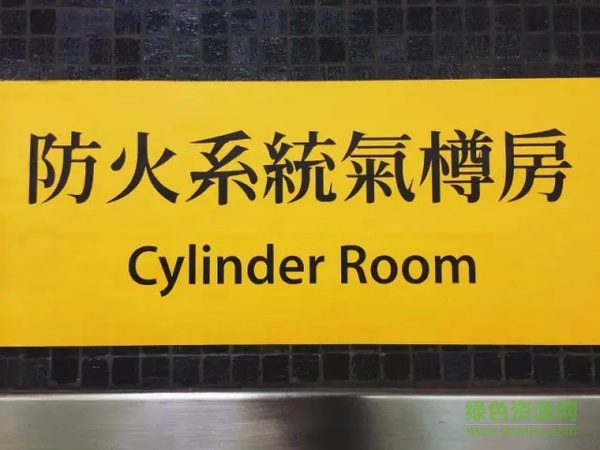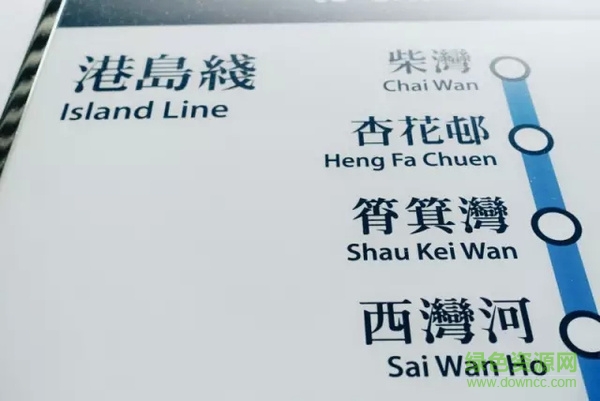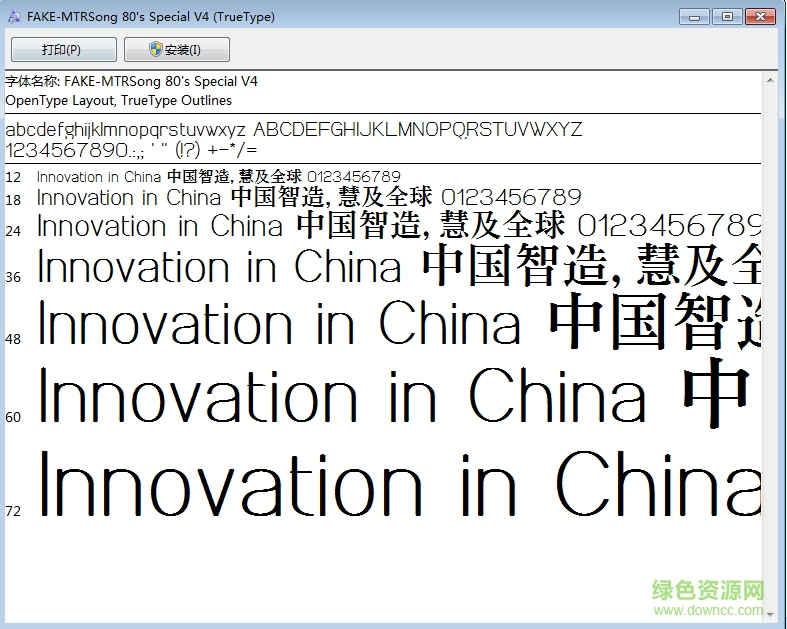
地鐵宋體是香港地鐵站所采用的書(shū)法字體,字跡清秀圓潤(rùn)充滿藝術(shù)美感,也是這個(gè)城市文化的相爭(zhēng),綠色資源網(wǎng)為大家?guī)?lái)最全的港鐵宋體合集,歡迎大家下載!
「地鐵宋一號(hào)」該是最為一眾地鐵列車(chē)迷、香港人所津津樂(lè)道的設(shè)計(jì),也是傳說(shuō)中的「MTRSong」字體。鉤劃尖銳鋒利,回筆處設(shè)計(jì)夸張、爽直而具設(shè)計(jì)感,風(fēng)格出眾。「地鐵宋一號(hào)」是為標(biāo)題用途而生的明體。這設(shè)計(jì)至今我們還可以在觀塘線一帶月臺(tái)墻身的警告字樣偶然看見(jiàn)。由于「地鐵宋一號(hào)」是照相排字字型,除了今天使用十分困難外、缺字也是一大問(wèn)題。所以港鐵近年已取儷宋與蒙納宋方便制作,逐步廢棄「地鐵宋」一號(hào)。
「地鐵宋二號(hào)」是一號(hào)的變體。其特色為比一號(hào)更為剛硬,去除無(wú)謂的修飾,也是筆者的心頭好。 「二號(hào)」多見(jiàn)于港島線、東涌線一帶玻璃幕門(mén)頂上的路徑指示,以及舊英制車(chē)身內(nèi)的路徑指示燈跟貼紙標(biāo)記。
「地鐵宋三號(hào)」筆劃圓潤(rùn)、充滿書(shū)法感,無(wú)論點(diǎn)劃、直鉤筆劃都帶有墨水造形,表情與「地鐵宋一號(hào)」相近,筆劃風(fēng)格卻完全不同。 「地鐵宋三號(hào)」沒(méi)有特定出現(xiàn)地點(diǎn),筆者至今發(fā)現(xiàn)多出現(xiàn)于垃圾桶標(biāo)記、幕門(mén)前貼上地上的警告紙,用途相對(duì)較飄忽。